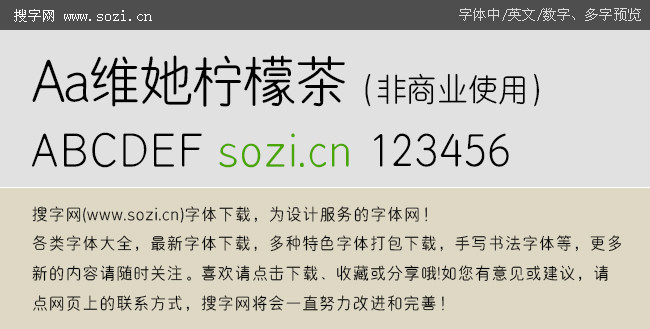
Aa維她檸檬茶
搜字網(wǎng)給大家提供一款A(yù)a維她檸檬茶(非商業(yè)使用)中文字體下載,該字體是一款簡(jiǎn)潔的藝術(shù)字體,字體空間分布均勻,筆觸粗細(xì)適中,清新簡(jiǎn)明。適合書裝設(shè)計(jì)、包裝設(shè)計(jì)、海報(bào)設(shè)計(jì)等應(yīng)用(此字體為個(gè)人非商用版,商用可以聯(lián)系QQ:1006760504)。